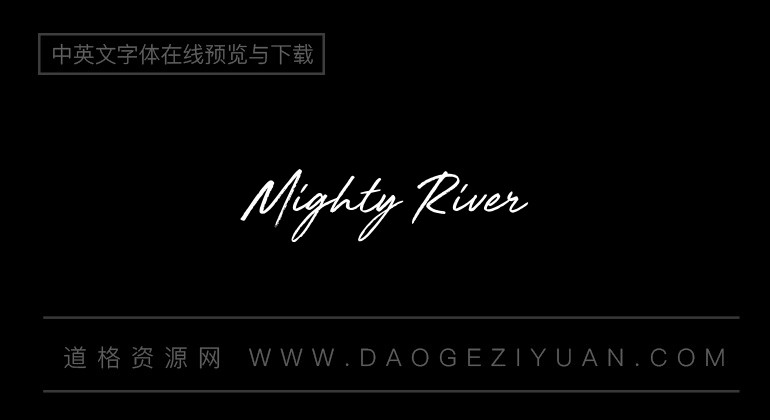
Mighty River
Mighty River 是一种非常流畅和现代化的字体,由美国设计师Paulo Goode 创造。这种字体被设计为既可用于标题和标志设计,又可用于段落文本。Mighty River 字体具有圆润的形状和柔和的曲线,同时又保持了强烈的可读性和清晰度。它的字符形状流畅自然,字母之间的间距和字重都非常匀称。这种字体非常适合用于品牌标志、印刷物和数字设计等多种设计用途。
Mighty River是一款非常不错的手写艺术字体,具有很好的视觉感,适合于文化类的宣传设计、商业类品牌的广告和产品包装设计以及个性化文字排版等较多场景。